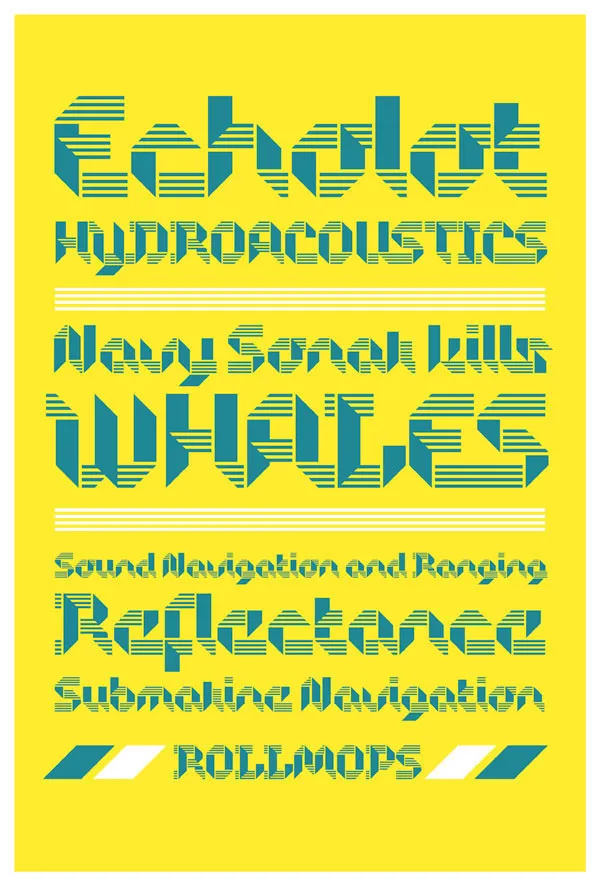
Rollmops Typeface – Download Grátis
A Rollmops Typeface é uma elegante tipografia do gênero Blackletter, criada pelo designer Hamilton para aqueles que valorizam a sofisticação e a história dessa tipologia tradicional. Com traços grossos e um tom poderoso, ela se destaca como uma opção perfeita para projetos históricos ou artesanais que precisam de um caráter único. Esta fonte não apenas oferece alegria aos olhos do leitor, mas também transmite uma sensação de profundidade e misticismo. Seja para gráficos em papel ou mídias digitais, Rollmops é uma excelente escolha para estilos que valorizam o passado com respeito e estilo moderno.